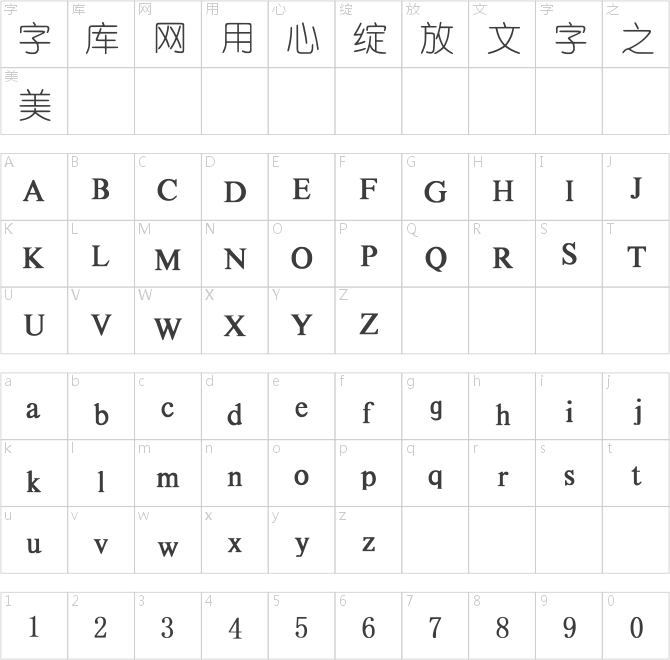
字體名稱: 蘭米細(xì)圓
蘭米細(xì)圓
蘭米細(xì)圓介紹
蘭米細(xì)圓字體字庫(kù)是一款讓人賞心悅目、百看不厭的中文字體,適合各類廣告和產(chǎn)品包裝設(shè)計(jì)應(yīng)用,字體大小4.43MB,格式為ttf字體,上傳用戶是雅迪,作者/版權(quán)方為蘭米字庫(kù)